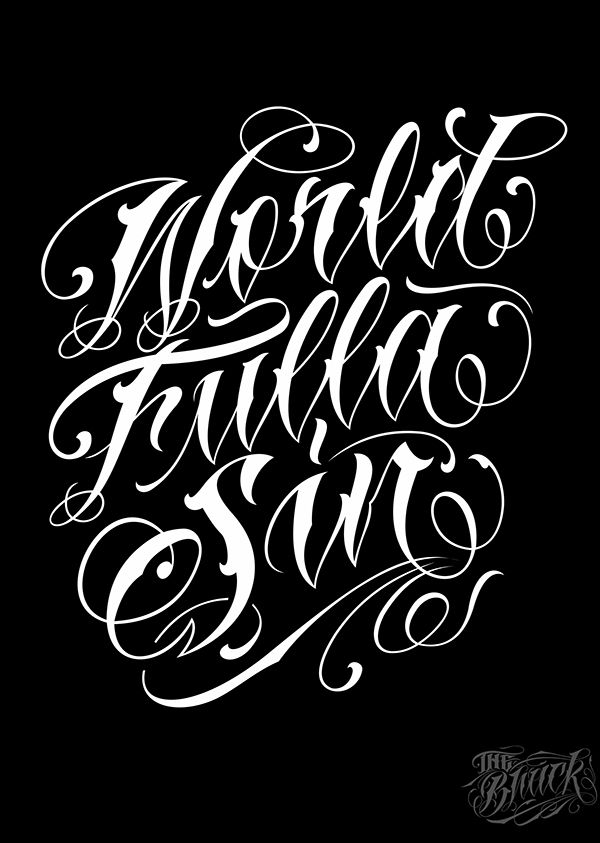
Шрифты и стили для начинающих
Важно различать стили и шрифты надписей. Если надпись является стилистическим, персонализированным оформлением, то шрифт определяется как набор символов и букв в одном стиле и размере. Несмотря на то что вы можете настроить кернинг и размер шрифтов, они менее гибки в работе, чем созданные собственноручно шрифты. Однако использование шрифта в качестве основы вместо создания каждой буквы с нуля позволит сэкономить время и найти новые идеи для собственных надписей. «Когда вы учитесь, то взять за основу общее начертание шрифта — неплохая идея, — говорит дизайнер и художник Робин Кейси. — Это дает вам ориентир, с чего можно начать, и вы можете использовать свою работу в качестве макета».
Знакомство с различными стилями надписей
Традиционная каллиграфия
Каллиграфия — это оформление и создание рукописного текста с помощью кисти или другого инструмента для письма. Традиционная каллиграфия охватывает определенные стили ручного письма, такие как Copperplate и Spencerian, которые отличаются определенными штрихами и формами.
Готический стиль
Одним из традиционных стилей каллиграфии является готический, иногда называемый «старопечатным». Этот стиль широко использовался в средневековой Европе, буквы рисовались широкими штрихами кистью сверху вниз. Он также использовался в первых печатных машинах. В настоящее время надписи в готическом стиле часто встречаются на татуировках или вывесках.
Современная каллиграфия
Современная каллиграфия — это любая форма каллиграфии, которая отличается более свободным и органичным начертанием. Рукописные надписи курсивом и кистью считаются современной каллиграфией, они способствовали росту ее популярности в недавнем прошлом. Хотя раньше каллиграфические надписи делались чернилами и пером на бумаге, новые приложения, такие как Adobe Fresco, принесли каллиграфию в цифровой мир.
Стиль с засечками
Засечки — это небольшие линии или отметки, которые добавляются на концах букв в определенных стилистических шрифтах.
Эти засечки иногда называют «хвостиками» или «ножками», и они могут придать надписи более формальный вид. Буквы с засечками также могут иметь красивый, стильный вид, если их украсить различными завитками.
Стиль без засечек
Все буквы без «хвостиков» относятся к стилю без засечек. Эти буквы имеют современный и четкий вид. К этой категории относятся такие стили, как монолайн (где все линии имеют одинаковую толщину) и блочные буквы (где буквы никогда не соединяются и не соприкасаются).
Новые стили надписей
В оформлении надписей происходят постоянные изменения и появляются новые тенденции. Взять, к примеру, различные стили, такие как надписи граффити или шрифты Баухаус, которые зародились в конкретных культурных направлениях, а затем стали использоваться самостоятельно. Текущие события влияют на дизайн, поэтому всегда следите за новыми шрифтами и стилями оформления надписей, появляющимися время от времени, чтобы не отставать от тенденций.
Как сделать потрясающую надпись с помощью цифровых инструментов
Создание надписей — это вид художественного искусства с огромными возможностями для творчества, особенно при использовании цифровых средств. Соответствующее программное обеспечение позволяет управлять каждой линией и кривой, чтобы получить точную форму букв в соответствии с замыслом проекта. Следующие руководства и рекомендации по созданию надписей помогут вам начать работу.
Я чувствую, что использование чего-то в realm из [style*="Arial"] было бы отправной точкой, но это все равно будет нацелено на все шрифты в стеке, не так ли?
Если вы установите базовый основной шрифт Arial bold, он будет резервным на большинстве клиентов email, за исключением Outlook, где резервный шрифт на самом деле Times New Roman.
Делая это, вы устанавливаете тело таблицы, ячейки таблицы, заголовки, размеры абзацев в Helvetica Neue. Если шрифт отсутствует, то по умолчанию используется стиль тела по умолчанию.
Это полный набор сокращенных шрифтов Helvetica Neue от Рейчел Мур. Вариация этого CSS может обеспечить вам нужный вам внешний вид. http://rachaelmoore.name/posts/design/css/web-safe-helvetica-font-stack/
Одна из проблем, которую я вижу, заключается в том, что ширина em шрифтов Helvetica Neue и Arial Bold действительно отличается, так что вы можете увидеть проблемы с макетом.